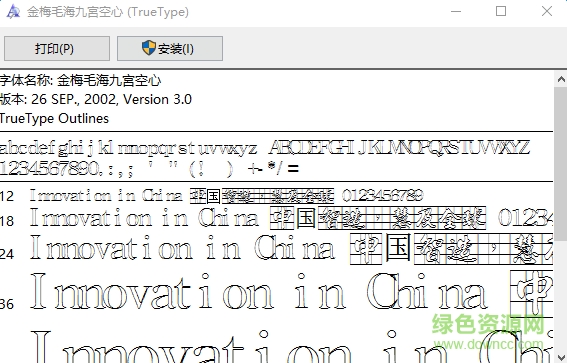
金梅毛海九宮空心字體是一款很有特色的字體,這款字體寫出來的字是空心的,和普通字體不一樣,而且字看起來顏色也很淺,可以用于藝術(shù)設(shè)計(jì)方面,歡迎有需要的朋友來綠色資源網(wǎng)下載。
這款字體小編覺得還是很好看的,寫出來的字很有自己的特色,是一款具有藝術(shù)風(fēng)格的字體,大家如果喜歡的話可以來綠色資源網(wǎng)下載。